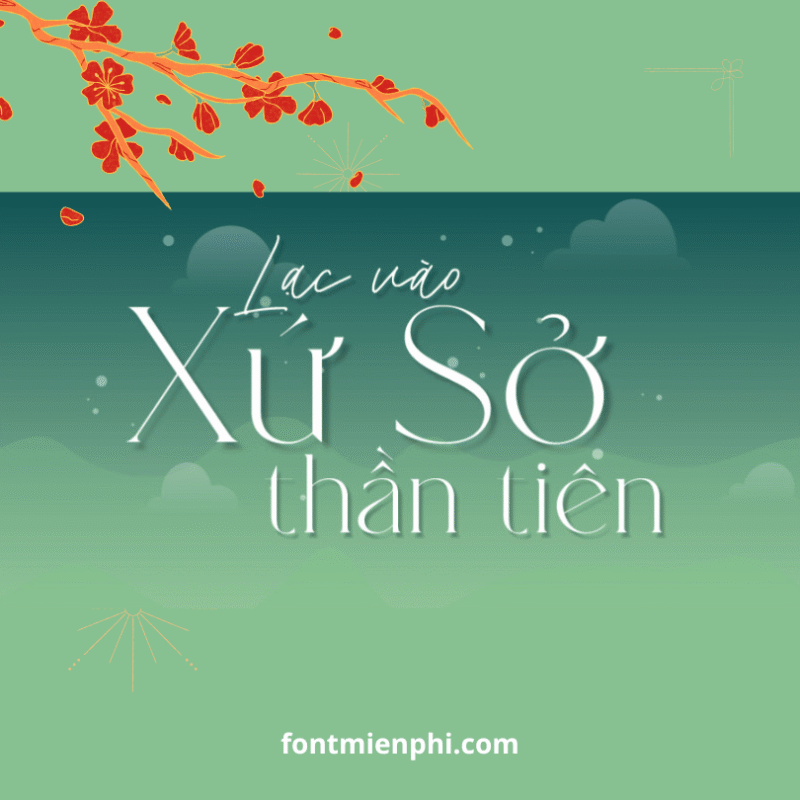
Font Việt hóa 1FTV VIP NT Seawave
Font Việt Hóa 1FTV VIP NT Seawave – Phong Cách Hiện Đại & Sang Trọng
1. Giới Thiệu Chung
1FTV VIP NT Seawave là một trong những font chữ Việt hóa cao cấp thuộc bộ sưu tập 1FirstFont (1FTV), được thiết kế với phong cách thanh lịch, hiện đại và tinh tế. Font chữ này phù hợp cho các dự án đòi hỏi sự chuyên nghiệp, từ thiết kế thương hiệu, bao bì, tạp chí đến các ấn phẩm digital cao cấp.
2. Đặc Điểm Nổi Bật
✔ Việt hóa hoàn chỉnh: Hỗ trợ đầy đủ bảng mã Unicode, bao gồm tất cả các ký tự tiếng Việt có dấu, đảm bảo hiển thị sắc nét trên mọi nền tảng.
✔ Phong cách sang trọng: NT Seawave sở hữu nét chữ mềm mại, uyển chuyển, kết hợp với các chi tiết tinh xảo, mang lại cảm giác quý phái và đẳng cấp.
3. Ứng Dụng Đa Dạng
• Thiết kế thương hiệu: Logo, namecard, bao bì sản phẩm.
• Truyền thông & Marketing: Banner, poster, standee, brochure.
• Digital Content: Website, social media, video intro.
• Ấn phẩm cao cấp: Tạp chí, menu nhà hàng, thiệp mời.
• Kết hợp với các font sans-serif như Montserrat, Helvetica để tạo sự cân bằng trong thiết kế.